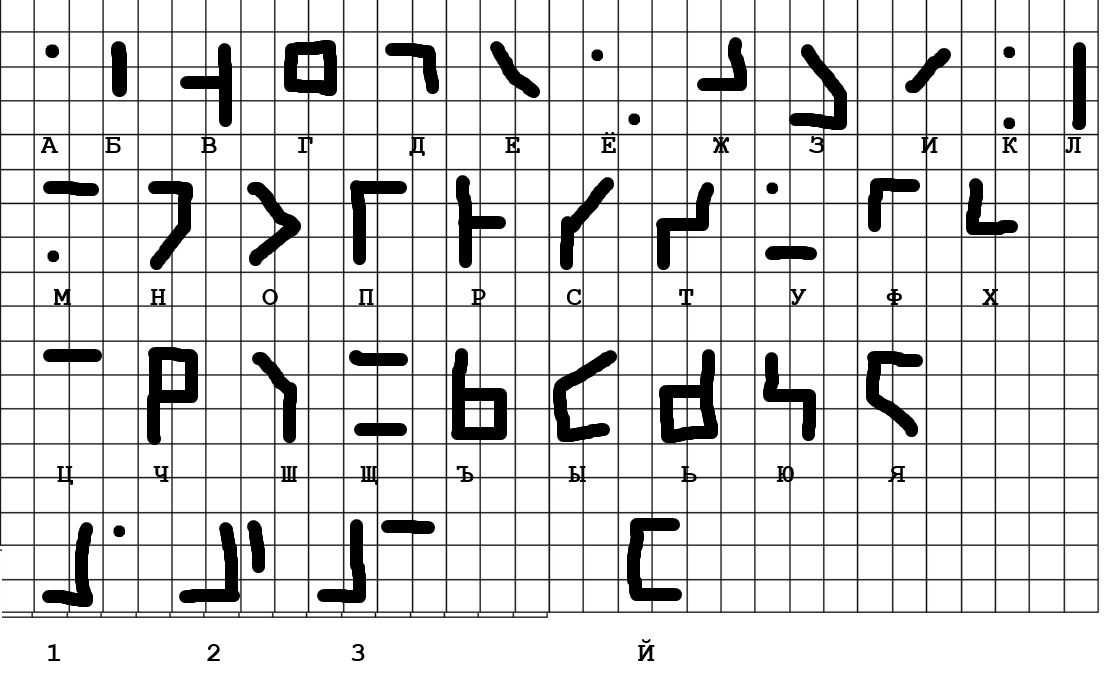
Шрифт Брайля для зрячих⁠⁠
Шрифт Брайля почему-то менее популярен чем азбука Морзе. Что странно, порог входа ниже, практической пользы больше.
Можно просто писать ручкой на бумаге. Или камешками. Или ямками. Или лампочками. Да как угодно.
И вот у меня появилась идея чтобы зрячие люди тоже могли общаться шрифтом Брайля. Без чтения пальцами, просто читать точки глазами. Устройства для чтения пальцами очень дорогие.
⠝⠁⠏⠗⠊⠍⠑⠗⠺⠕⠞⠞⠁⠅⠺⠕⠞
Практическая польза:
Записать что-то для себя чтобы другие не прочитали сходу
Или сделать малозаметную шпаргалку
Социальная польза тоже есть: больше людей знают об шрифте, может это где-то кому-то поможет.
Как выучить шрифт Брайля?
Просто взять и выучить. Всего 33 буквы, боже мой. Сокращений как в английском Брайле у нас нет. Да, поначалу будете тупить и забывать, но через пару дней практики это пройдёт.
А чтобы не забывать, можно общаться с помощью него.
Для вот этого, последнего, я сделал сайт с парочкой тренажёров для запоминания, чатом и телеграм-бота.
На сайте можно писать как с клавиатуры буквами, так и сразу точками. Можно потренировать как отдельные буквы (игра), так и чтение новостных заголовков. Кодировать, раскодировать, и ещё общаться. В телеграме только общение: исходящие пишем русскими буквами, зато входящие всегда шрифтом Брайля.
читать шрифт брайля глазами - это возможно, но книгу (с двусторонней рельефной печатью) хрена с два можно нормально читать.
Если адаптировать шрифт брайля для зрячих, то я в детстве так пыталась. Получалось что-то вроде как так... Но проще использовать шрифт Муна, например.
Шрифт Муна вживую нигде не видел (в отличие от шрифта Брайля), а учить ещё один шрифт только для того чтобы писать самому мало смысла.